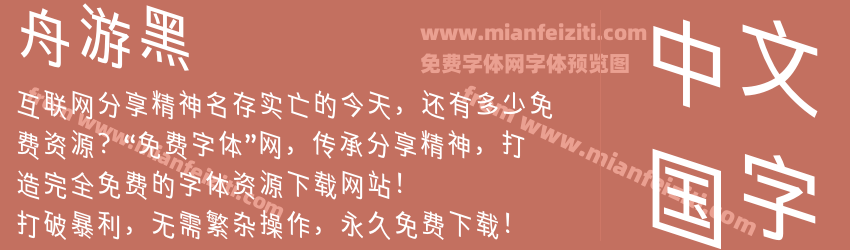
为了方便整活运动,我还做了个倾斜角度与明日方舟相同的黑体 ArknightSans,原打算命名为明日方舟黑(仿微软雅黑),但问题在一这是商标、二如果舟游真有人要做个类似腾讯体的商标黑体,会导致名称撞车使软件无法调用,于是参考字游工房出品的游黑体(Yu Gothic,游ゴシック,视窗和Mac系统自带)就叫“舟游黑”,正好字体日文名也是现成的。
本款“舟游黑”是一款书写很新颖的字体,字体大方,适合各种设计作品使用!欢迎下载!